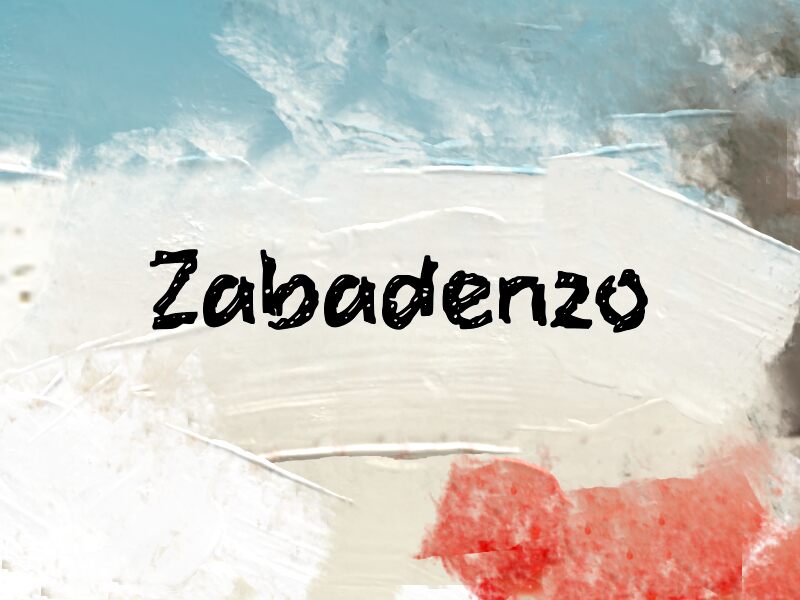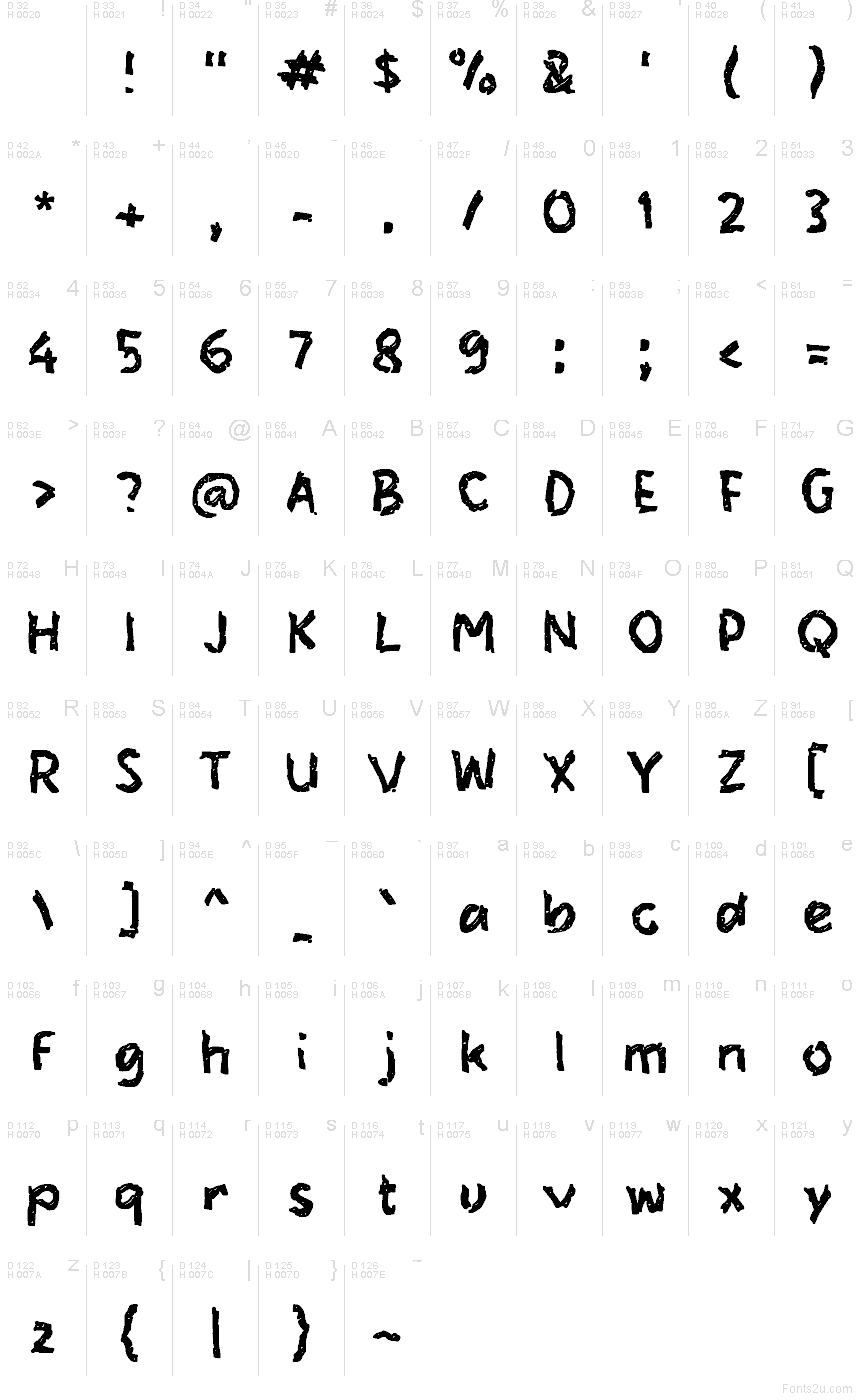
Zabadenzo od Wep to darmowy krój pisma w stylu surowego pędzla, przypominający ręcznie malowane stemple. Litery są grube, swobodne i lekko nierówne, z poszarpanymi krawędziami i drobnymi ubytkami, co nadaje im suchego, „tłustego” charakteru – wyglądają jak ręcznie tworzone, a nie cyfrowo wygładzane.
Świetnie sprawdza się w nagłówkach plakatów, brandingu kawiarni, oprawie muzyki niezależnej, okładkach książek i zabawnym opakowaniu, gdzie ta specyficzna tekstura pędzla gra pierwsze skrzypce. Jako darmowy font, Zabadenzo idealnie pasuje do grafik w mediach społecznościowych, plansz tytułowych i krótkich haseł w stylu logo, szczególnie gdy zależy Ci na swobodnym, nieco „niechlujnym” i pełnym życia efekcie.